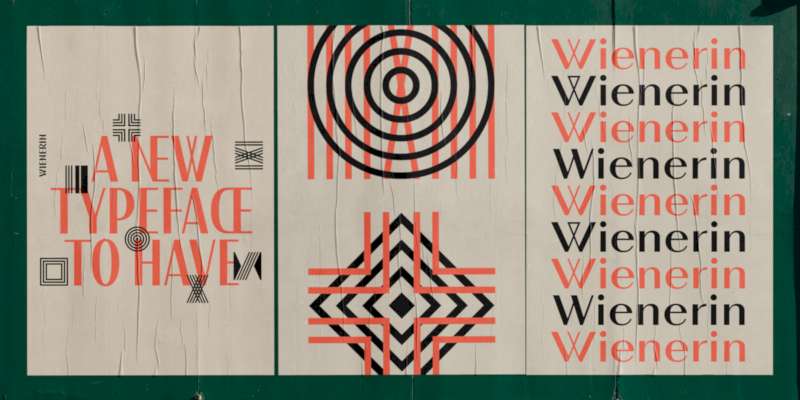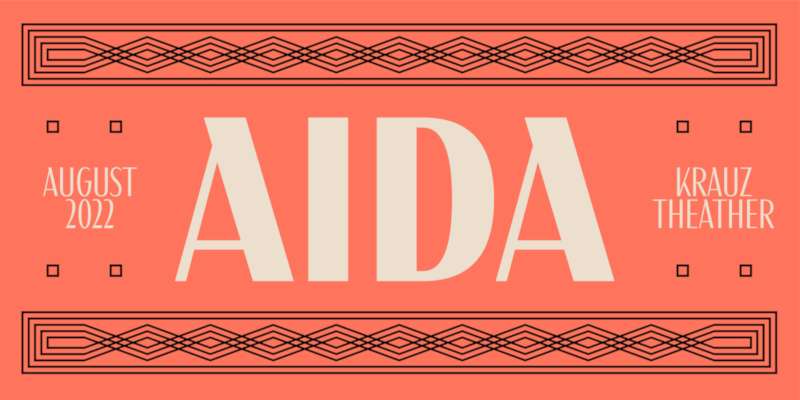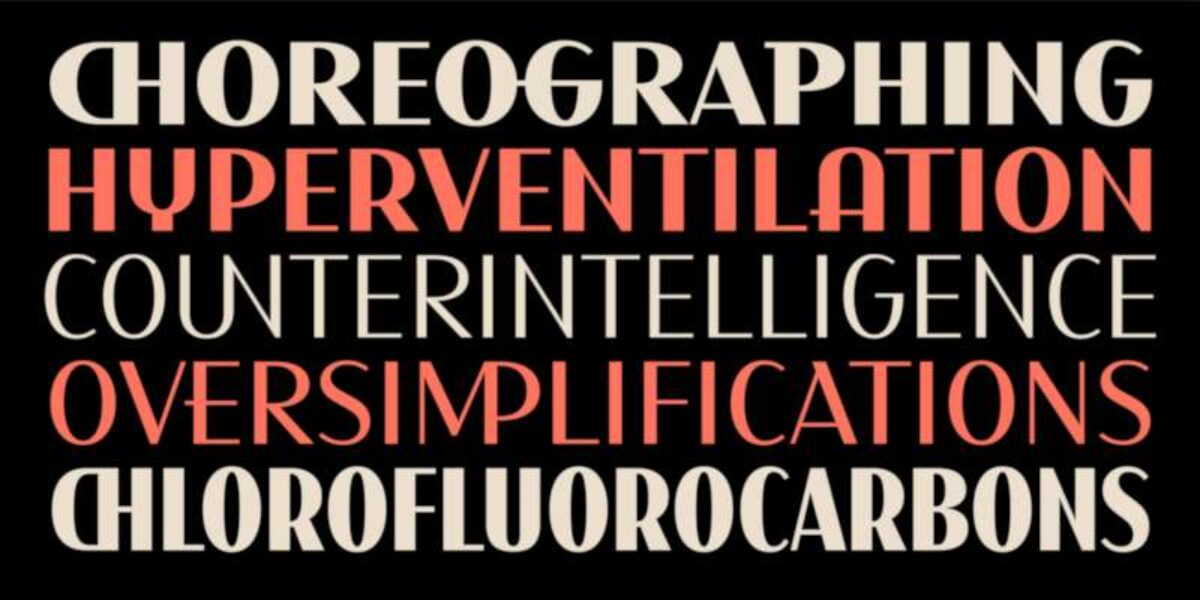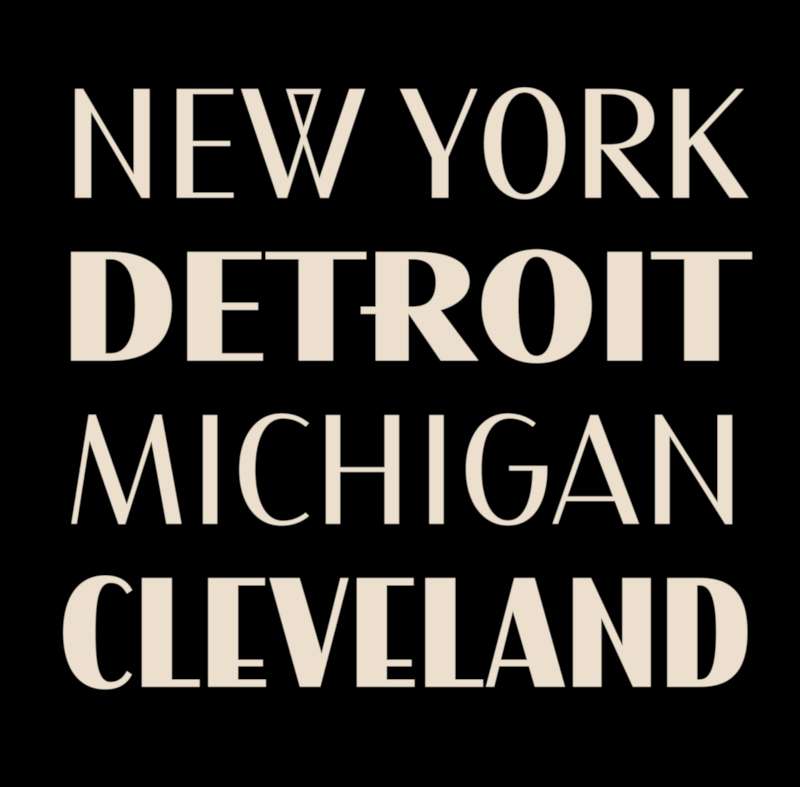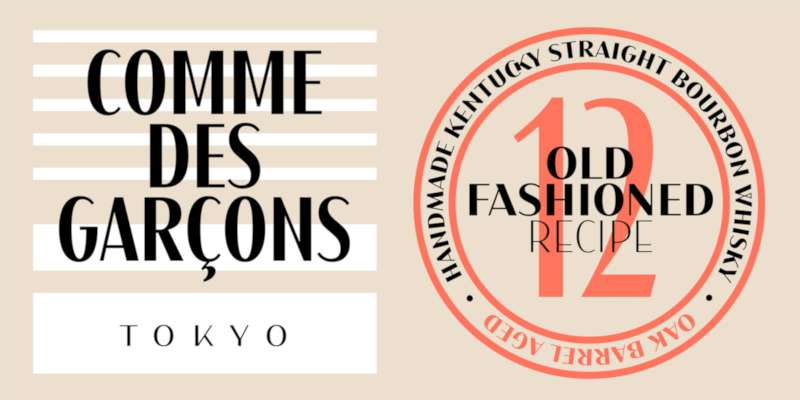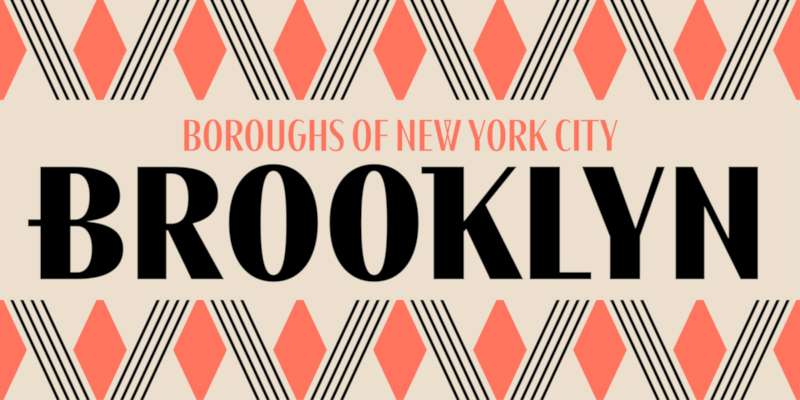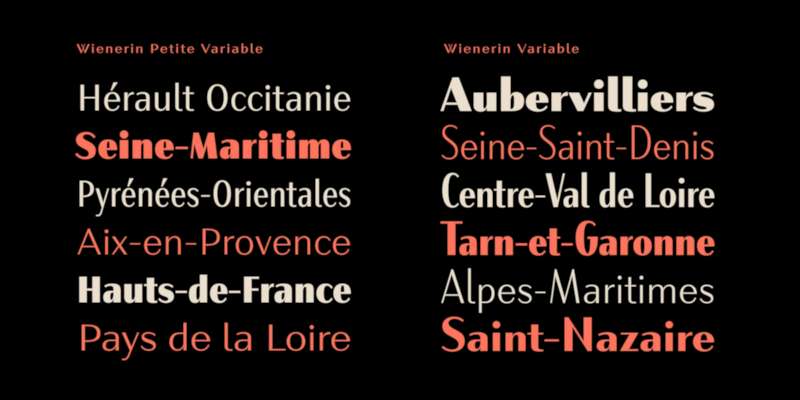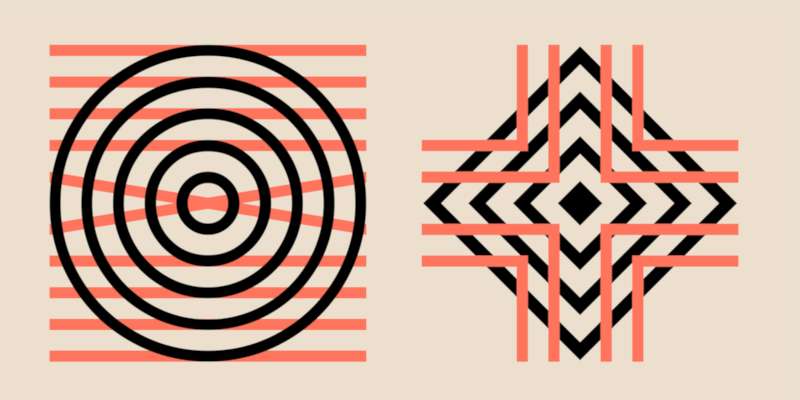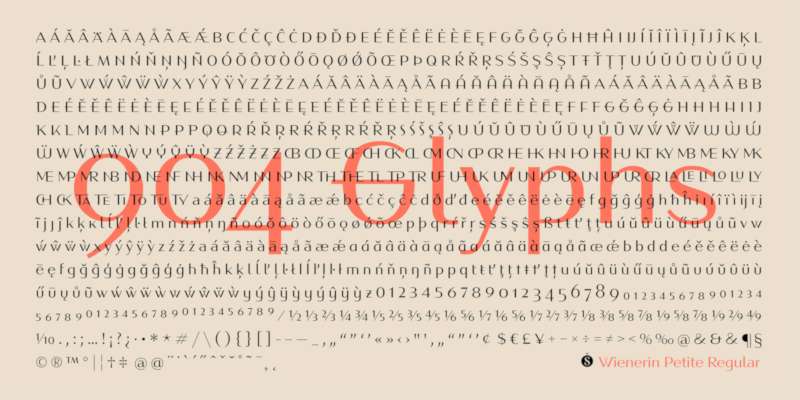
Wienerin é a nova fonte criada por Ale Paul do Sudtipos
Wienerin é o nome da nova fonte criada por Ale Paul do Sudtipos. Essa fonte foi criada inspirada no trabalho do designer e artista austríaco Carl Otto Czeschka, que fazia parte da The Wiener Werkstätte. Essa era uma associação de designers, arquitetos e outros artistas que existiu na Áustria no início do século vinte.
A Wienerin é uma expansão e revisão de uma fonte chamada Olympia que foi criada por Carl Otto Czeschka há mais de 100 anos. Só que, aqui, Ale Paul resolveu adaptar o trabalho original para o uso contemporâneo tendo vários sinais e ligaduras adicionadas. Tudo isso porque Ale Paul resolveu aproveitar as novas possibilidades que estão disponíveis quando se trata de fontes variáveis.
Uma das características adicionada a Wienerin devido a essa tecnologia de fontes variáveis é a forma com a qual foram criados modulos diferentes para criar molduras. São quase 500 molduras diferentes disponíveis em três pesos variados.
Outra característica da Wienerin é como o seu design foi criado de forma alongada. Assim, uma versão da fonte foi criada com um x-box maior do que o normal com a ideia de permitir um uso mais amplo de toda a família de fontes.
A Wienerin vem com um contraste diferente, por isso mesmo, ela é ideal para ser usada em peças que demandam um visual delicado. Perfeita para o design editorial, a criação de papelarias sofisticadas e moda. Ou seja, se você está procurando uma fonte inspirada na Art-Nouveau e repleta de variações visuais, essa pode ser a fonte que você estava procurando.